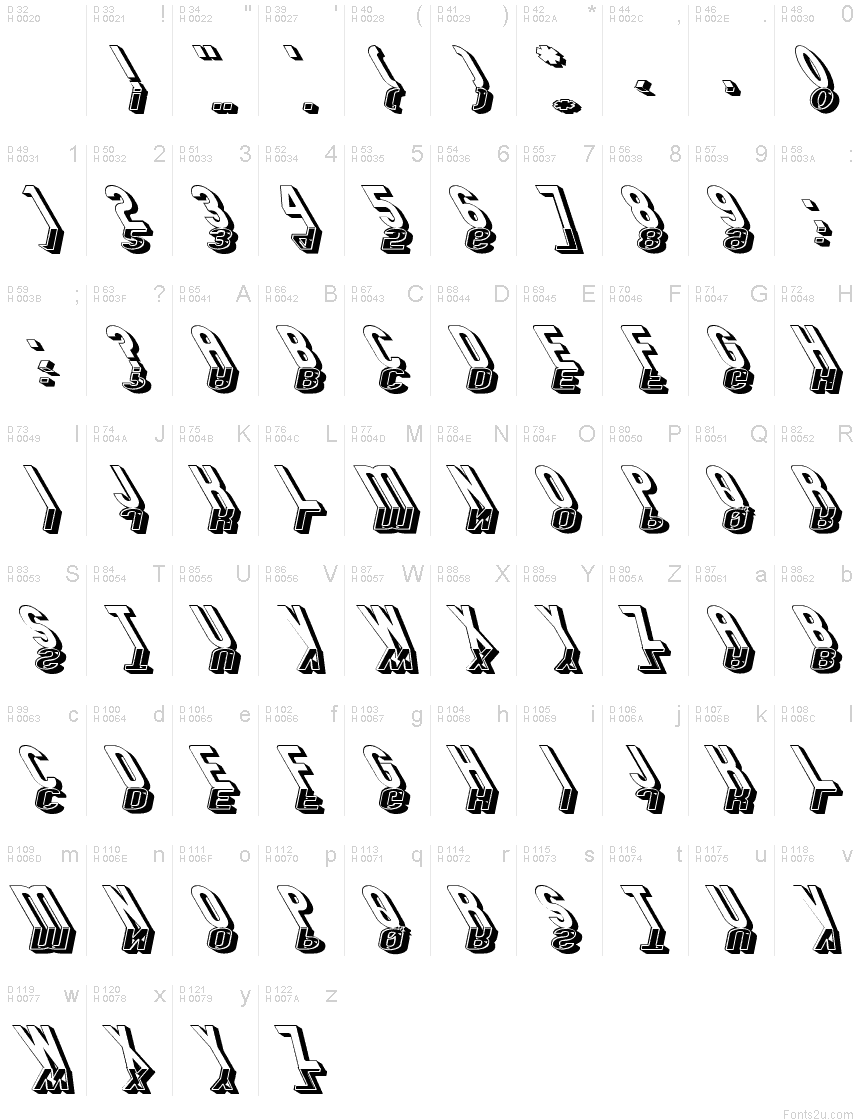
GM Exp Shadow Gravestone3 od G.M. to darmowy, trójwymiarowy krój displayowy, który przyciąga wzrok niczym stos grubych, pochylonych bloków. Masywne, białe litery zamknięte w głębokich czarnych konturach z wyraźnymi cieniami tworzą efektowny, wielowarstwowy wygląd – jednocześnie retro i lekko złowieszczy, przypominający stare komiksy grozy lub nocne szyldy wesołych miasteczek. Silne pochylenie w przód dodaje dynamiki, sprawiając, że każde słowo zdaje się wyskakiwać z kartki.
GM Exp Shadow Gravestone3 sprawia, że duże nagłówki stają się natychmiast bardziej wyraziste, bliskie i dramatyczne. Świetnie sprawdza się na plakatach, grafikach halloweenowych, w logotypach gier, brandingu streetwearowym, miniaturach YouTube czy eventowych ulotkach. Ten darmowy font najlepiej prezentuje się w dużym rozmiarze, gdzie jego masywne cienie mogą w pełni wybrzmieć. W przypadku tekstów uzupełniających, połącz go z czystym, neutralnym krojem bezszeryfowym, aby zachować pełne skupienie na jego odważnych formach 3D.
GM Exp Shadow Gravestone3